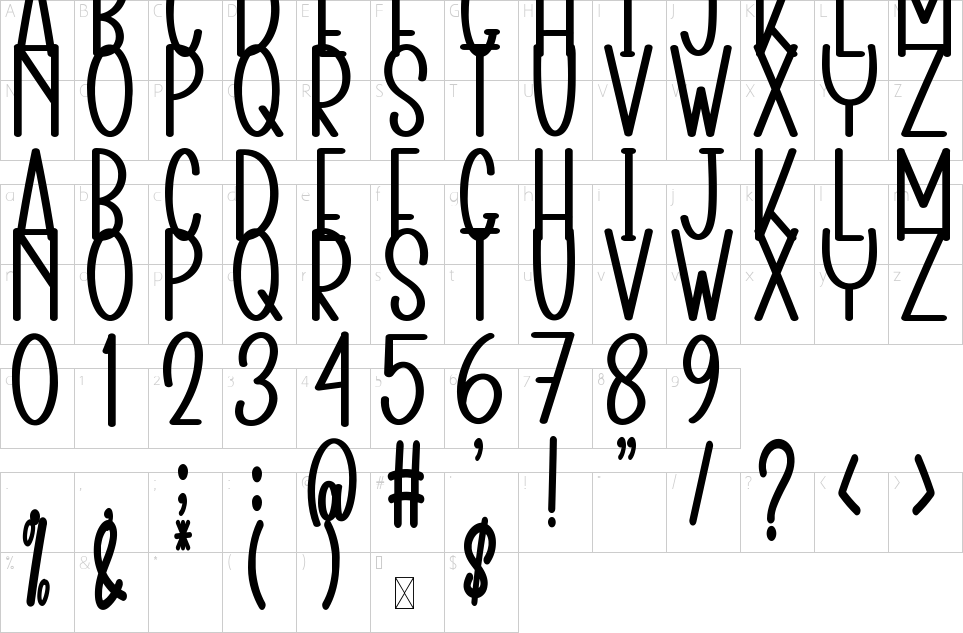
Daily Thinking Font – Download Grátis
A Daily Thinking Font é uma fonte de estilo casual e versátil projetada especificamente para quem busca uma pausa leve na rotina diária. Suave e confortável, essa fonte é ideal tanto para um trabalho cotidiano quanto para qualquer projeto pessoal que deseja adicionar um toque casual ao texto. Desenvolvida pela InermediaSTUDIO, esta fonte tem a capacidade de dar um novo fôlego à sua escrita diária, oferecendo uma maneira amigável e eficaz de incorporar um pouco mais de personalidade no seu cotidiano. Com 395 downloads já registrados, percebe-se que os usuários encontram grande valor nessa fonte única e fácil de usar. Seja para assinaturas, design gráfico ou simplesmente escrever no computador em casa, Daily Thinking Font pode ser um recurso indispensável na sua coleção de ferramentas digitais gratuitas.